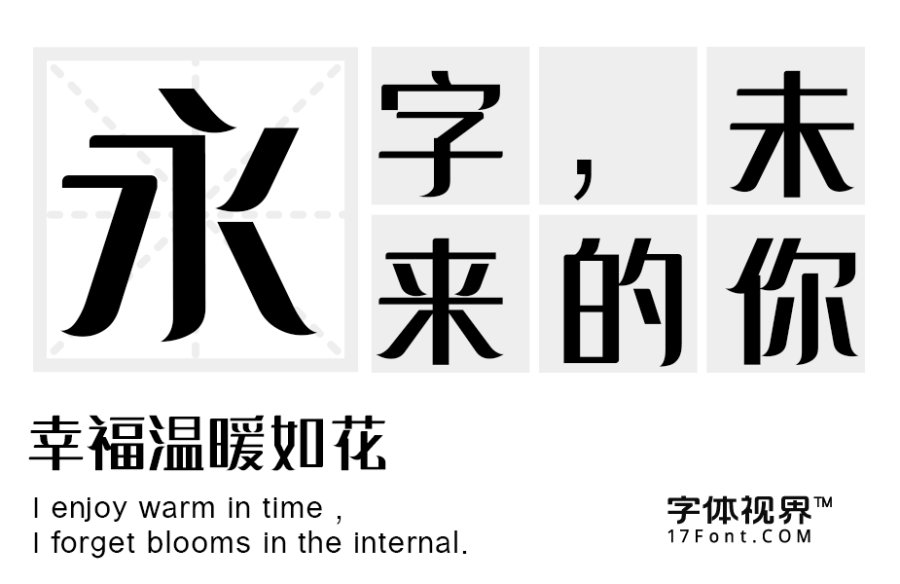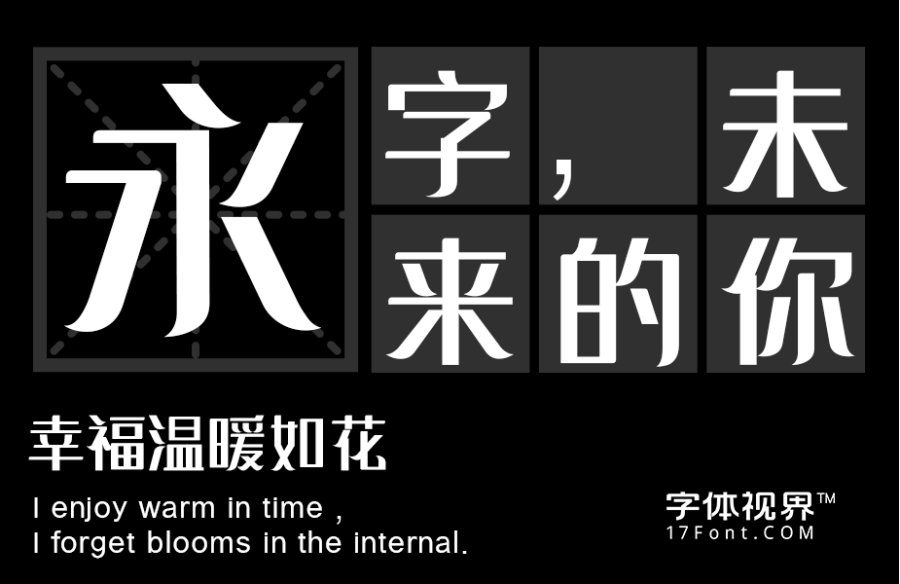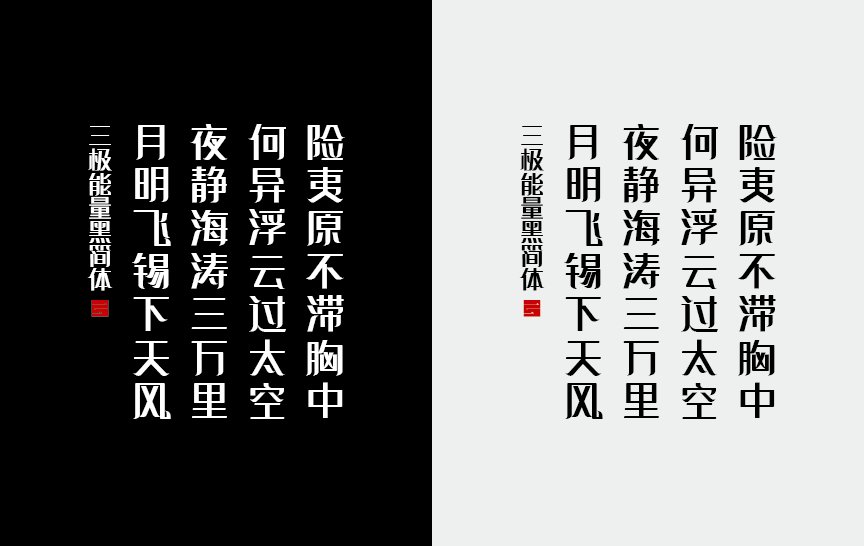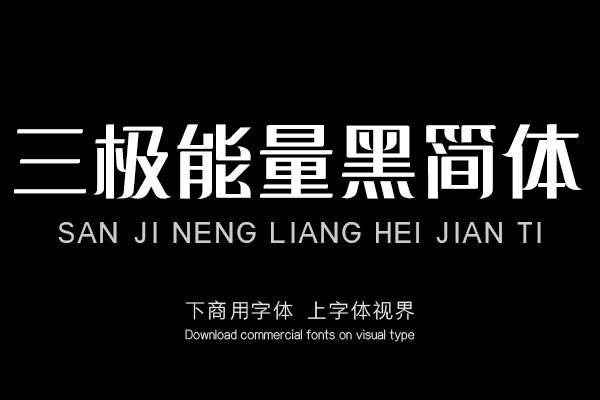
三极能量黑简体整体用了矩形与弯角两种图形元素来构建,起笔局部做圆弧处理,把笔画概括成飘逸的弧形,并且使左右笔画适当展开尽量对称,最大限度地简化笔画造型。字体结构......购买须知:“下载服务费”与“字体VIP”所获得字体 仅用于个人非商用, 商用请联系付费授权。本字体为电脑用字,手机没有root权限不支持直接手机换字(手机如何root,请自行百度搜索教程)。购买前请先 了解清楚后再付款 ,字体为虚拟产品无法回收 一旦购买不支持退款。